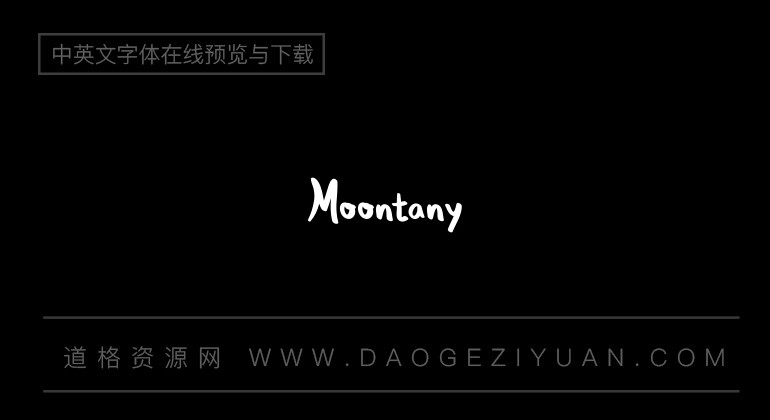
Moontany
Moontany 字体是一种流畅、现代化的字体,由 Moon(月亮)和 Tany(山脉)两个单词组合而成,灵感来自于大自然的美丽和神秘。 Moontany 字体有多种字重和风格,包括常规、粗体、斜体等。它的设计风格简洁明了,每个字母都具有独特的特点,不仅易于阅读,还具有美感。因此,它广泛应用于品牌标志、海报、广告、包装设计等领域。 该字体由一位名为 Gatis Vilaks 的设计师设计,它还包括大量的特殊字符和标点符号,以满足不同场景和语言的需求。Moontany 字体适用于中英文等多种语言,是一种功能齐全、设计精美的字体。
Moontany是一款非常不错的手写艺术字体,具有很好的视觉感,适合于文化类的宣传设计、商业类品牌的广告和产品包装设计以及个性化文字排版等较多场景。